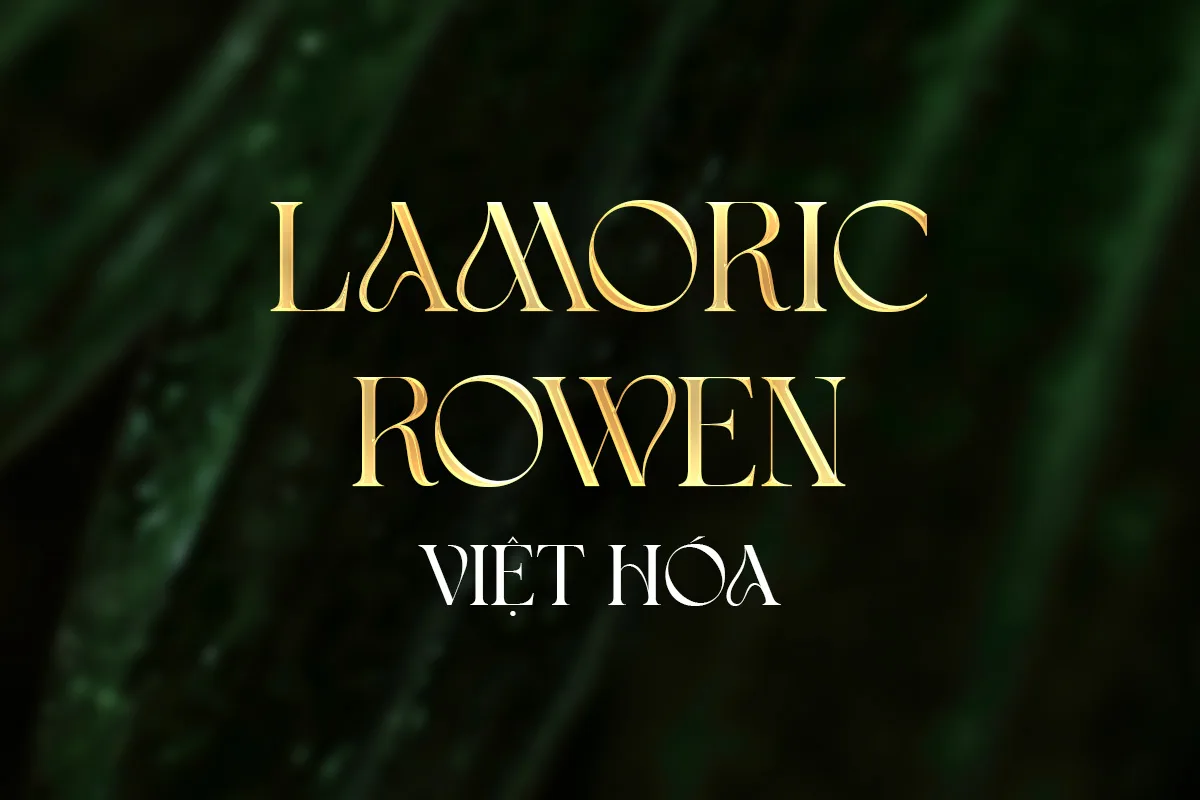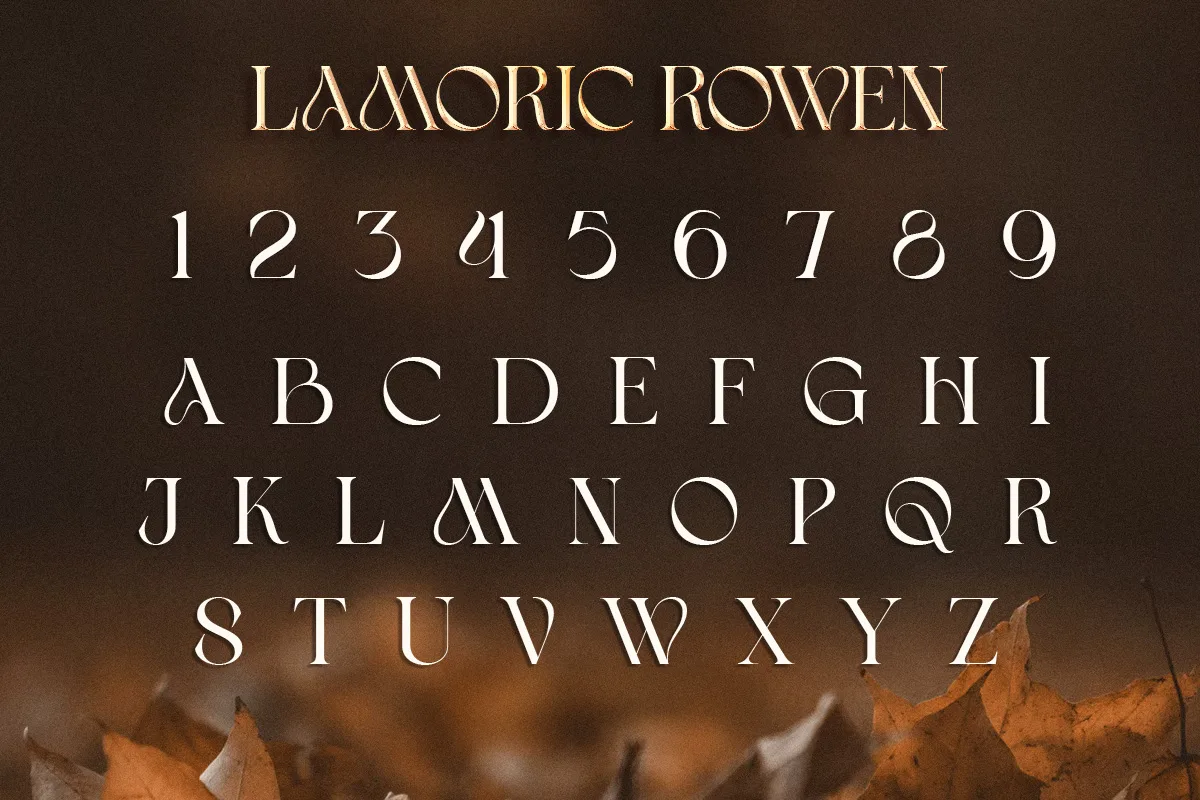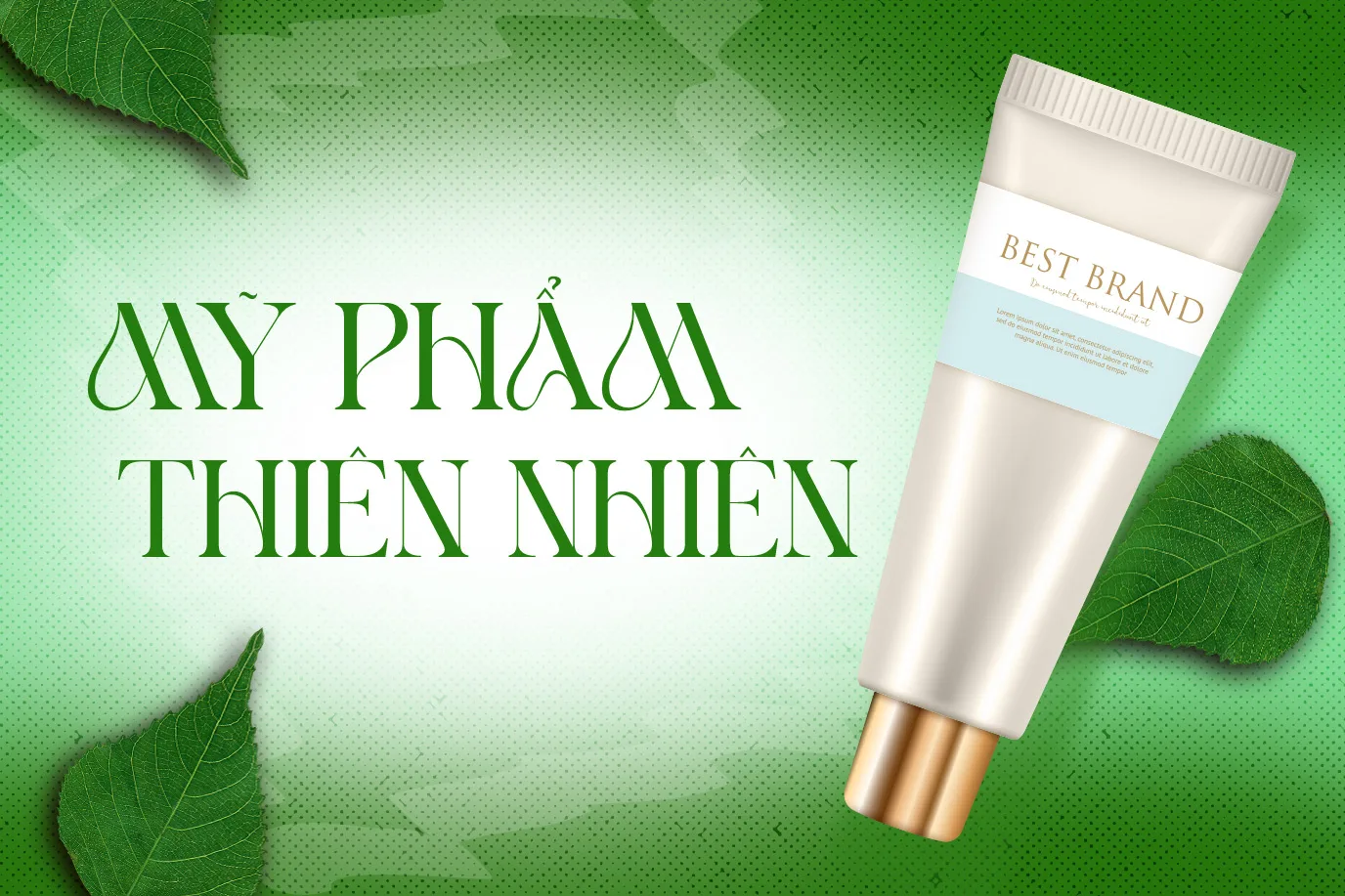
DVN Lamoric Rowen Việt hóa – Font chữ uốn lượn cách điệu thanh lịch, tự nhiên và đầy cá tính
DVN Lamoric Rowen Việt hóa là một kiểu chữ serif hiện đại với đường nét uốn lượn tinh tế, mang lại cảm giác vừa sang trọng vừa độc đáo. Các chi tiết bo tròn và đường cong mềm mại gợi liên tưởng đến thiên nhiên, phù hợp với các thiết kế cần sự hài hòa và cao cấp như thương hiệu mỹ phẩm, thời trang, bao bì sản phẩm hữu cơ, logo hoặc ấn phẩm quảng cáo cao cấp.
Font được Việt hóa đầy đủ dấu và ký tự tiếng Việt, đảm bảo tính ứng dụng trong thiết kế thương hiệu tại Việt Nam. Sự kết hợp giữa vẻ cổ điển của serif và hơi thở đương đại giúp DVN Lamoric Rowen trở thành lựa chọn lý tưởng cho những dự án muốn thể hiện sự tinh tế, tự nhiên nhưng vẫn đầy cá tính.
👉 Thích hợp dùng trong: Logo, packaging, editorial design, poster mỹ phẩm, thương hiệu cao cấp.